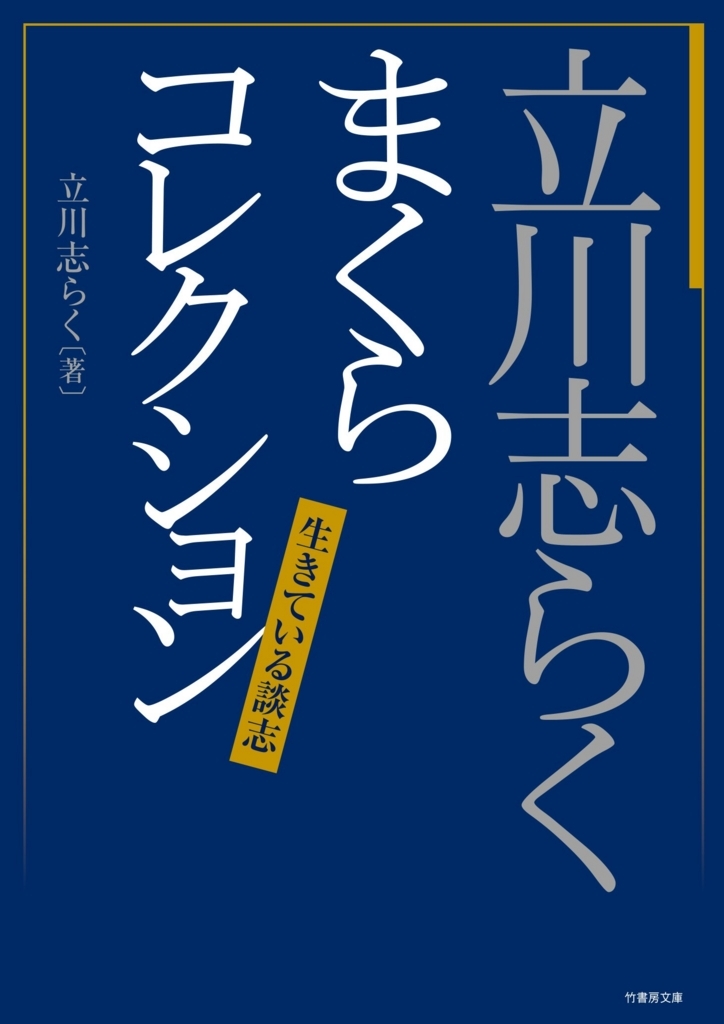
立川志らく まくらコレクション 生きている談志
「するってぇと、お前さん何かい? まくらが変わると眠れないってかい」
落語の噺は、マクラ・本題・落ちで構成されており、まくらは本題への導入部分として
のいわば掴みの部分で安眠するため同様に大事な存在だ。
落語のまくらは、本題に入るための流れを作ったり、本題で分かりにくい言葉の説明などが入ったりするわけであり、今回の記事においてもこの部分がまくらだ。
近年は芸能界のご意見番としてブレイク中の「立川志らく」
本名は新間一弘(しんまかずひろ)。1963年8月16日生まれの東京都出身。落語家であり、映画監督(日本映画監督協会所属)、また映画評論家、昭和歌謡博士、劇団主宰、TVコメンテーターなど幅広い肩書きで活動中。
1985年10月立川談志に入門。1988年二つ目昇進、1995年真打昇進。現在弟子20人を超える大所帯となっている。
特に近年では、コメンテーターとしてブレイクして、現在は芸能界のご意見番のような存在として発言がメディアに取り上げられる事も多いが、落語の才能も非凡。志らくについて、生前に師匠である立川談志からも「落語家の中で才能ならば志らくが一番」と評されていた。
その落語立川流の立川志らくが落語で語ったまくらを集めたまくら集が「立川志らく まくらコレクション 生きている談志」である。
立川談志無くして、立川志らくも無いと言えるほどの談志への愛が毒舌交じりに語られる。
落語家立川志らくを形成する骨、肉、血すべてが立川談志で溢れていることが分かる、立川志らくを通して談志も好きになるそんな一冊。
ちなみに私は電子書籍で本書を読んだ。
「なにぃ? するってぇと、お前さんは何かい? エレキ書籍で読んだってのかい?
そりゃぁまたずいぶんとハイテクなこった!」
オチもなく、とくにお後もよろしくはないようだが本書の紹介はここまで。
寄席に客を集めるための江戸文字「寄席文字」
さて、落語といえば寄席文字だ。
寄席文字は通称橘流と呼ばれる寄席で使用される江戸文字の一種で寄席に客を集めるための寄席ビラの「ビラ字」が発祥。
上記と下記の寄席文字のフォント(書体)はダイナコムウェアが販売しているDC寄席文字を使用した。
立川志らくの著書「志らくの言いたい放題」
立川志らくの兄弟子・立川談春の視点から描いた立川談志「赤めだか」もオススメ
立川志らくの兄弟子ににあたり、近年は俳優としての評価も高まる立川談春が、師匠である立川談志の下での修業時代を綴ったエッセイ。発行後、ベストセラーになり、後にテレビドラマ化して放送もされた人気の一冊。
もちろん弟弟子である立川志らくも登場する。談春のエッセイで書かれた志らくは若干鼻もちならないキザな男ではあるが…。